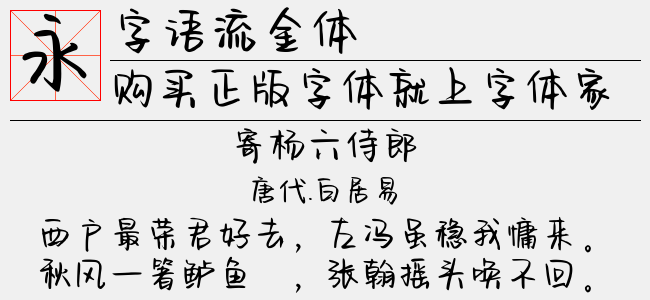
字语流金体(5.40 MTTF中文字体下载)
字语流金体 字体大小5.40 M,包含了6763个汉字以及附加其他英文字体和阿拉伯数字,属于字语字库。字语流金体(TTF)可以免费下载,商业用途请自行购买版权,它的特征就是书法,手写,海报,个性,采用安装嵌入的安装方式,支持符号拉丁文日文中文等语言
字体名称:字语流金体